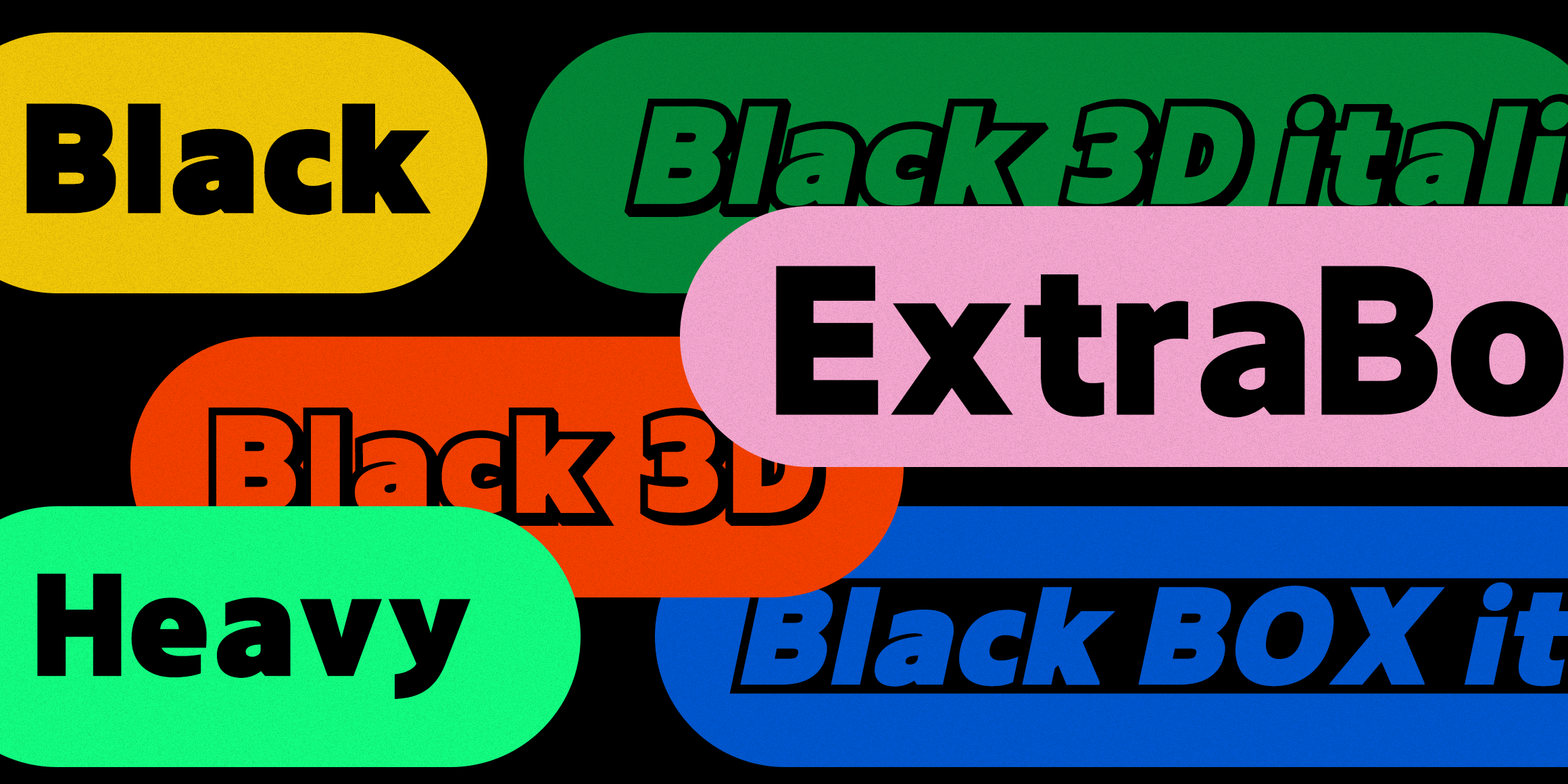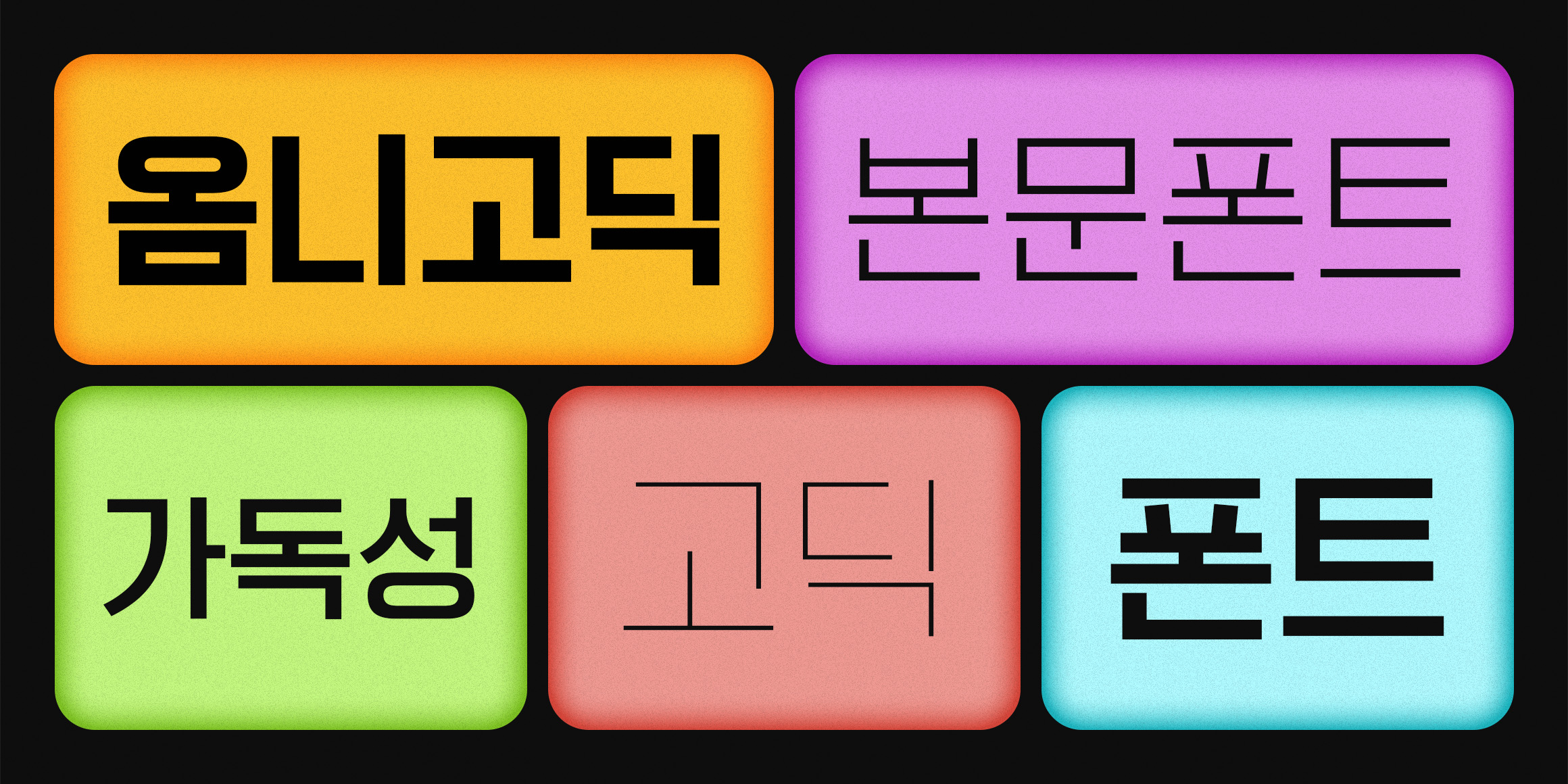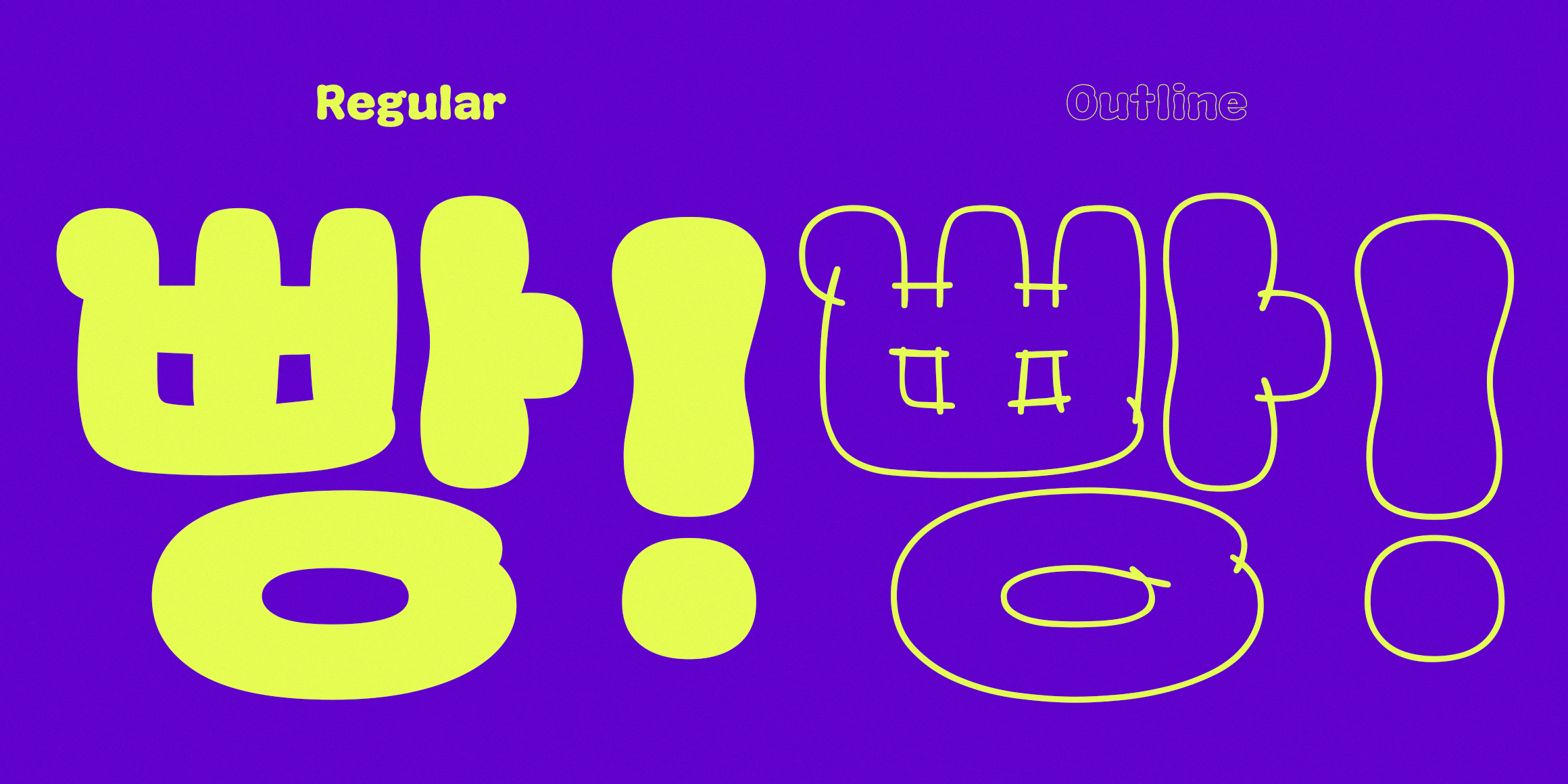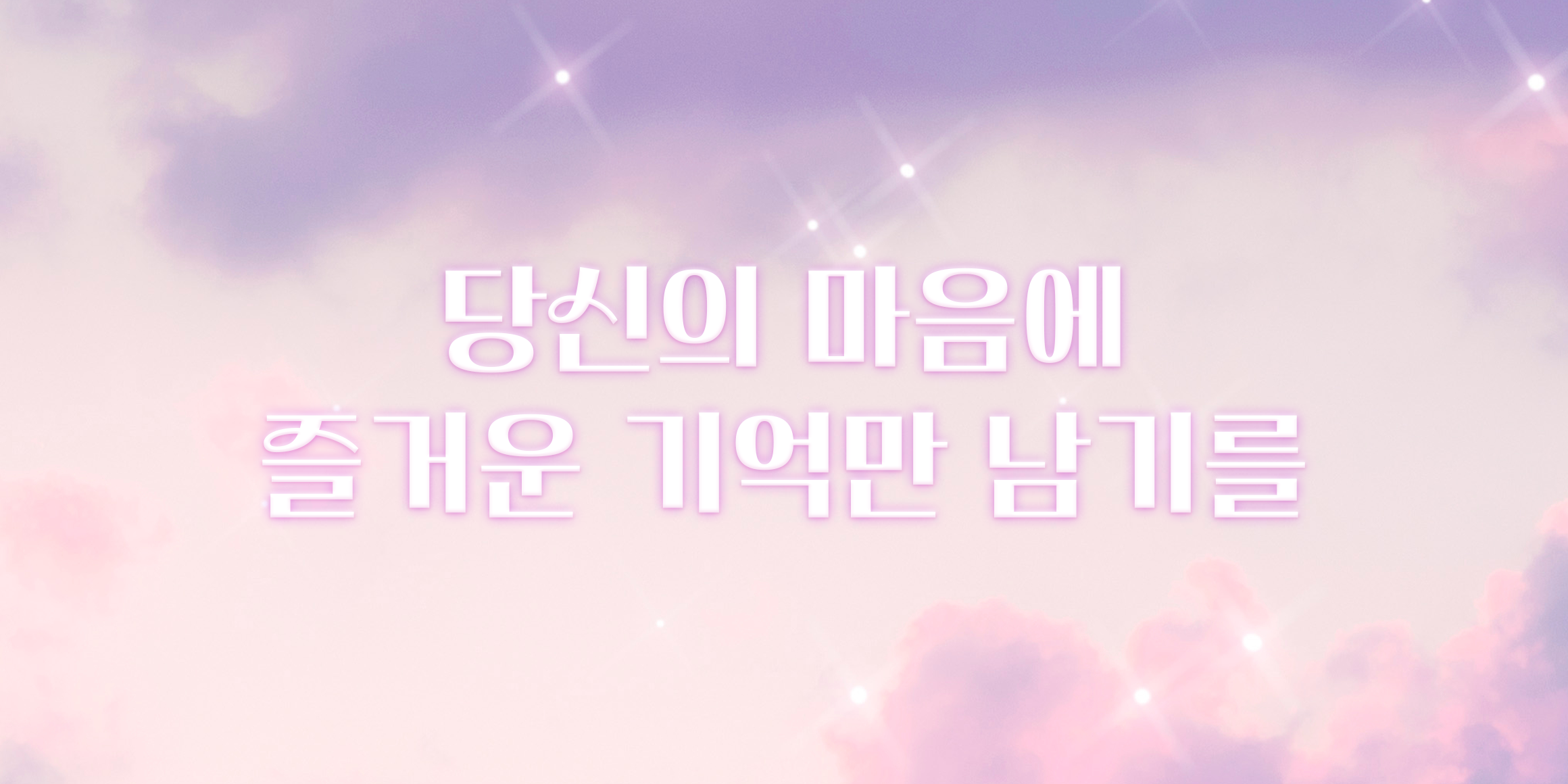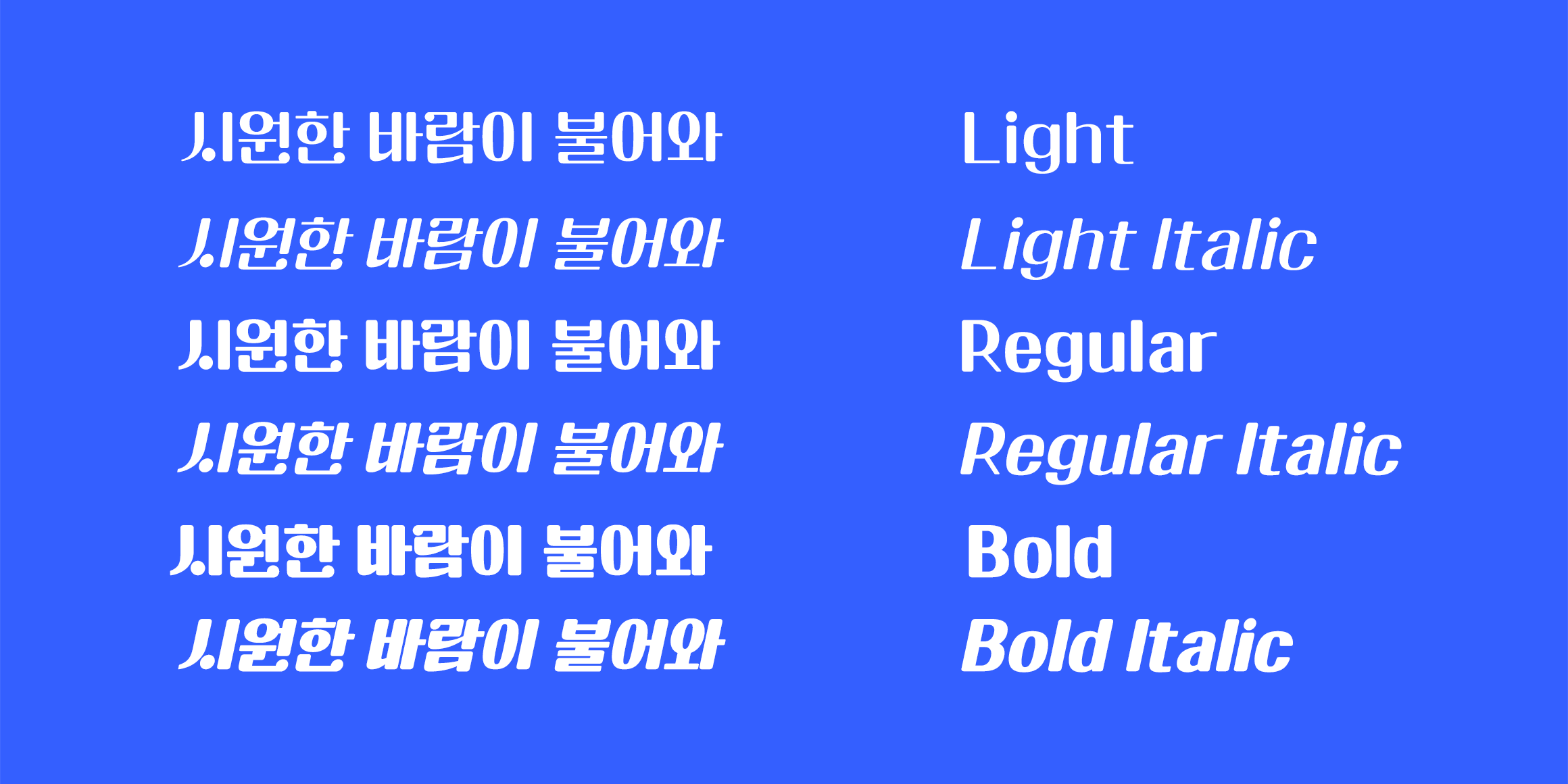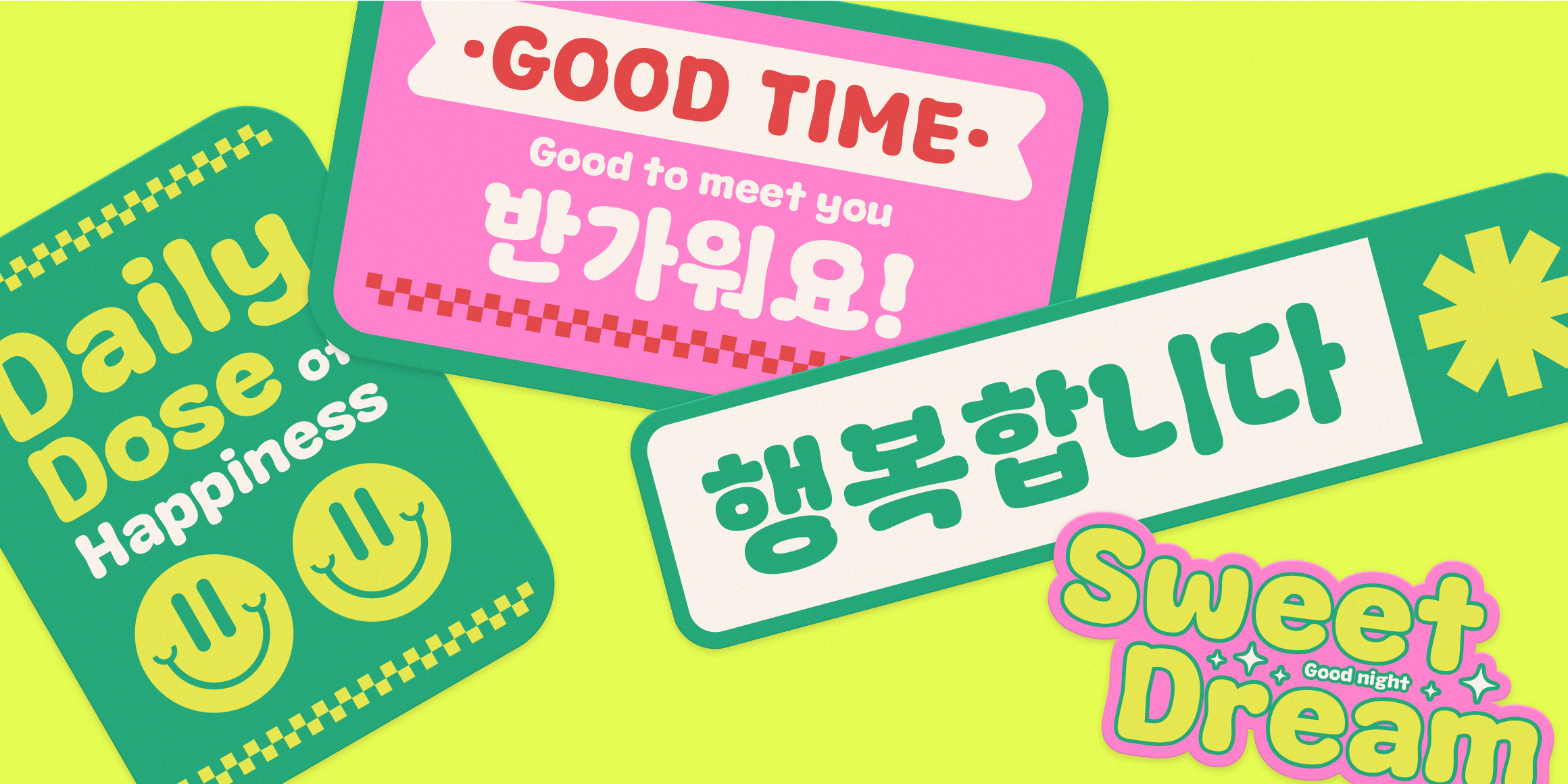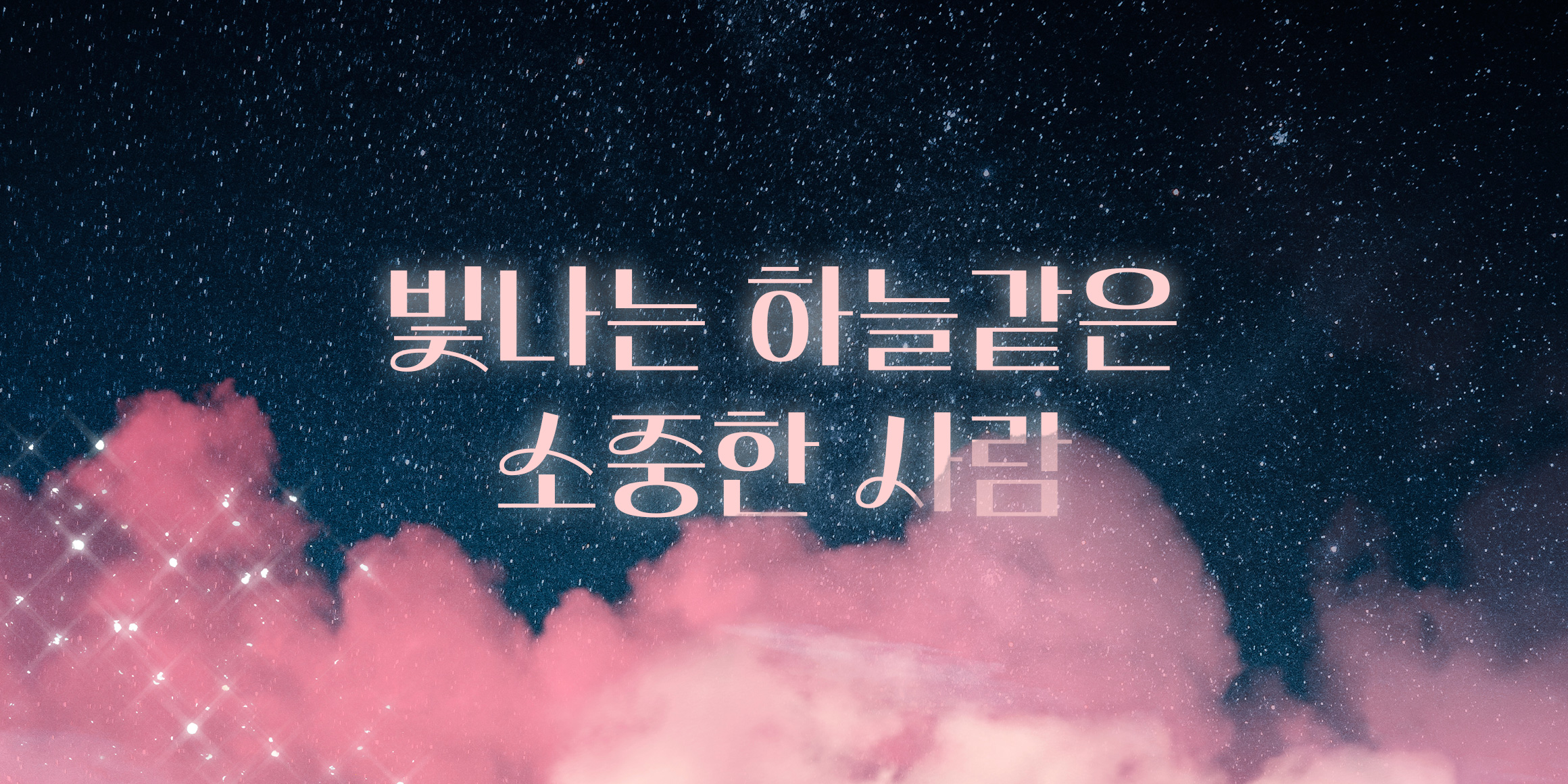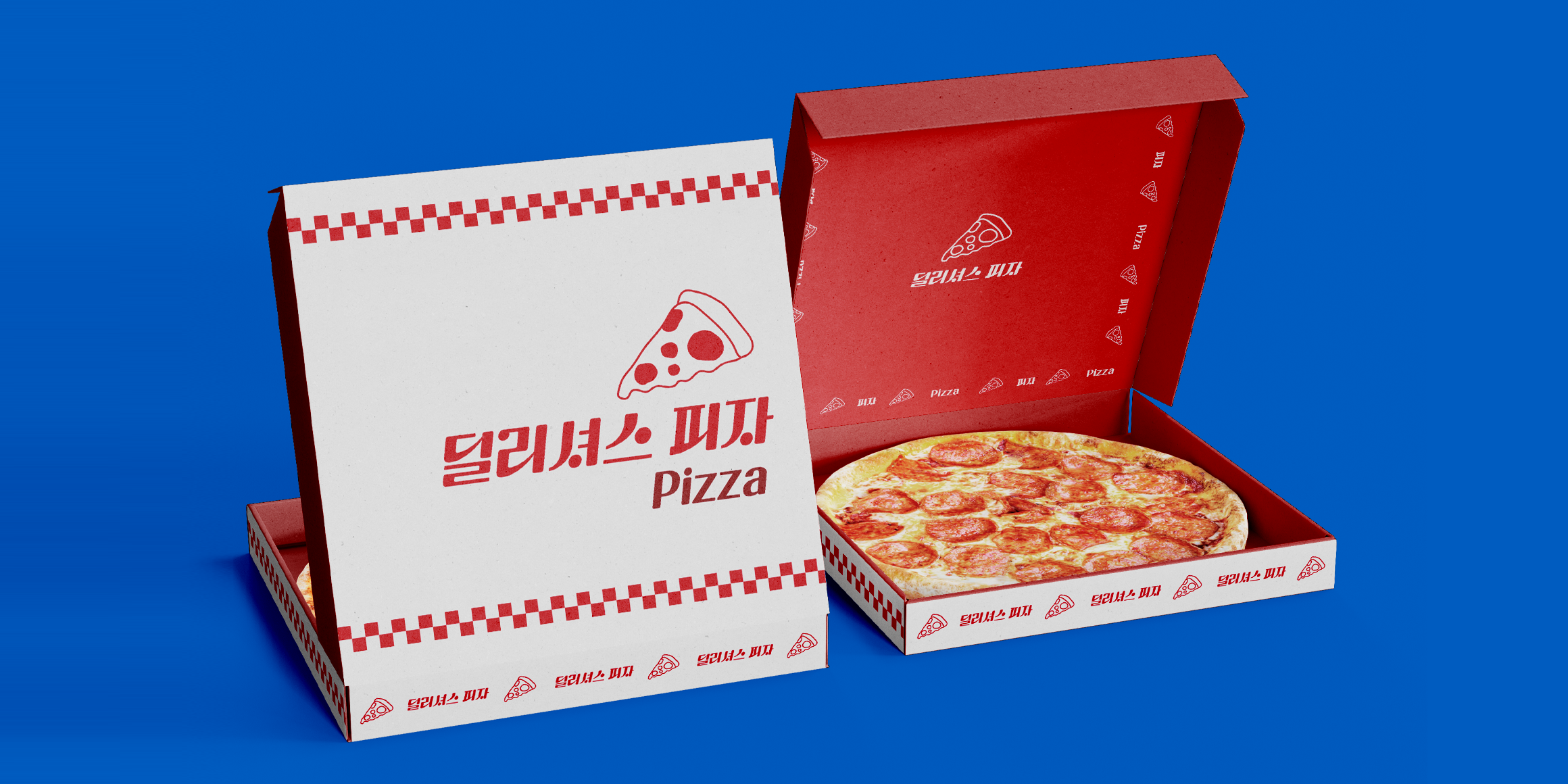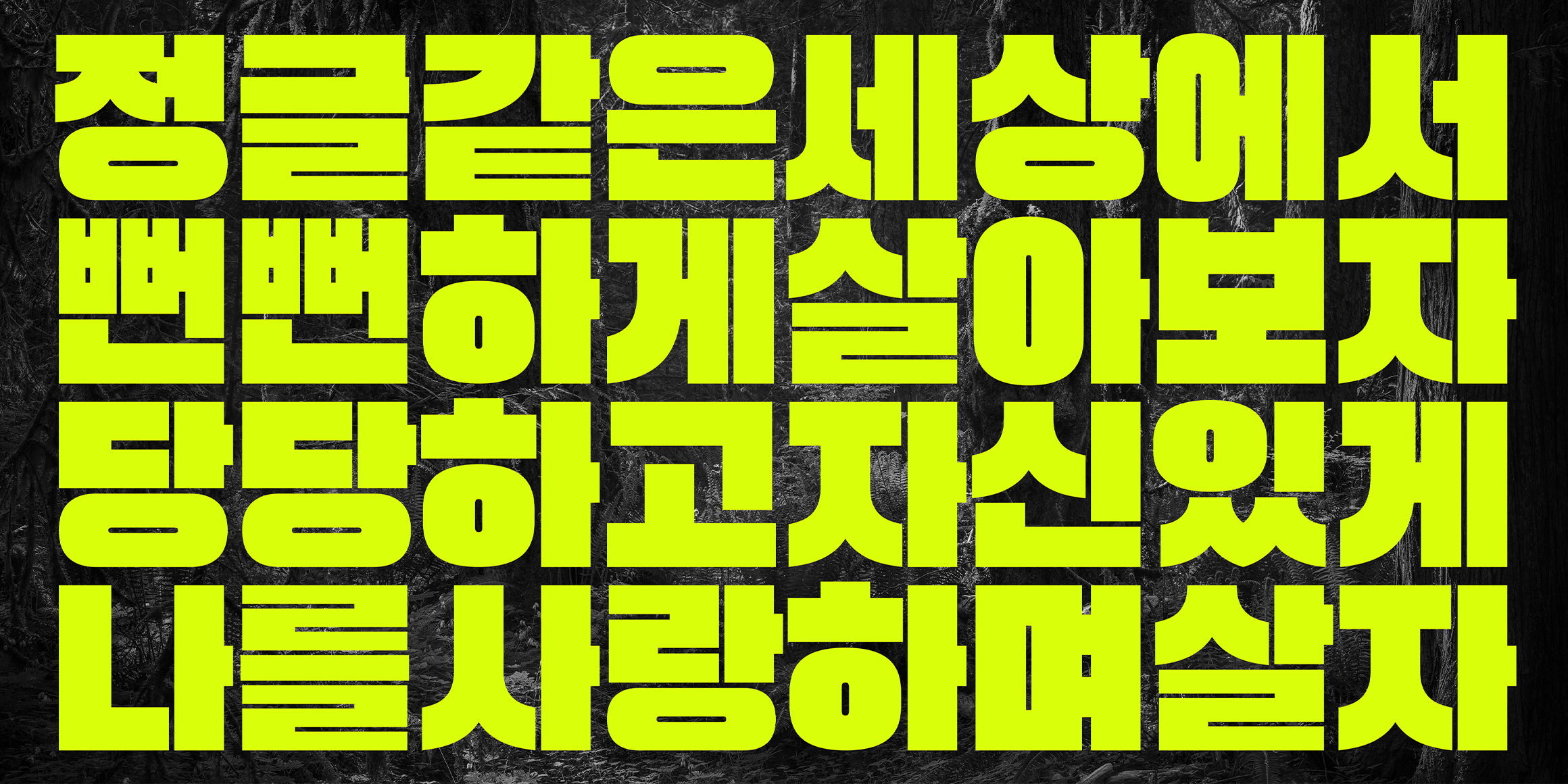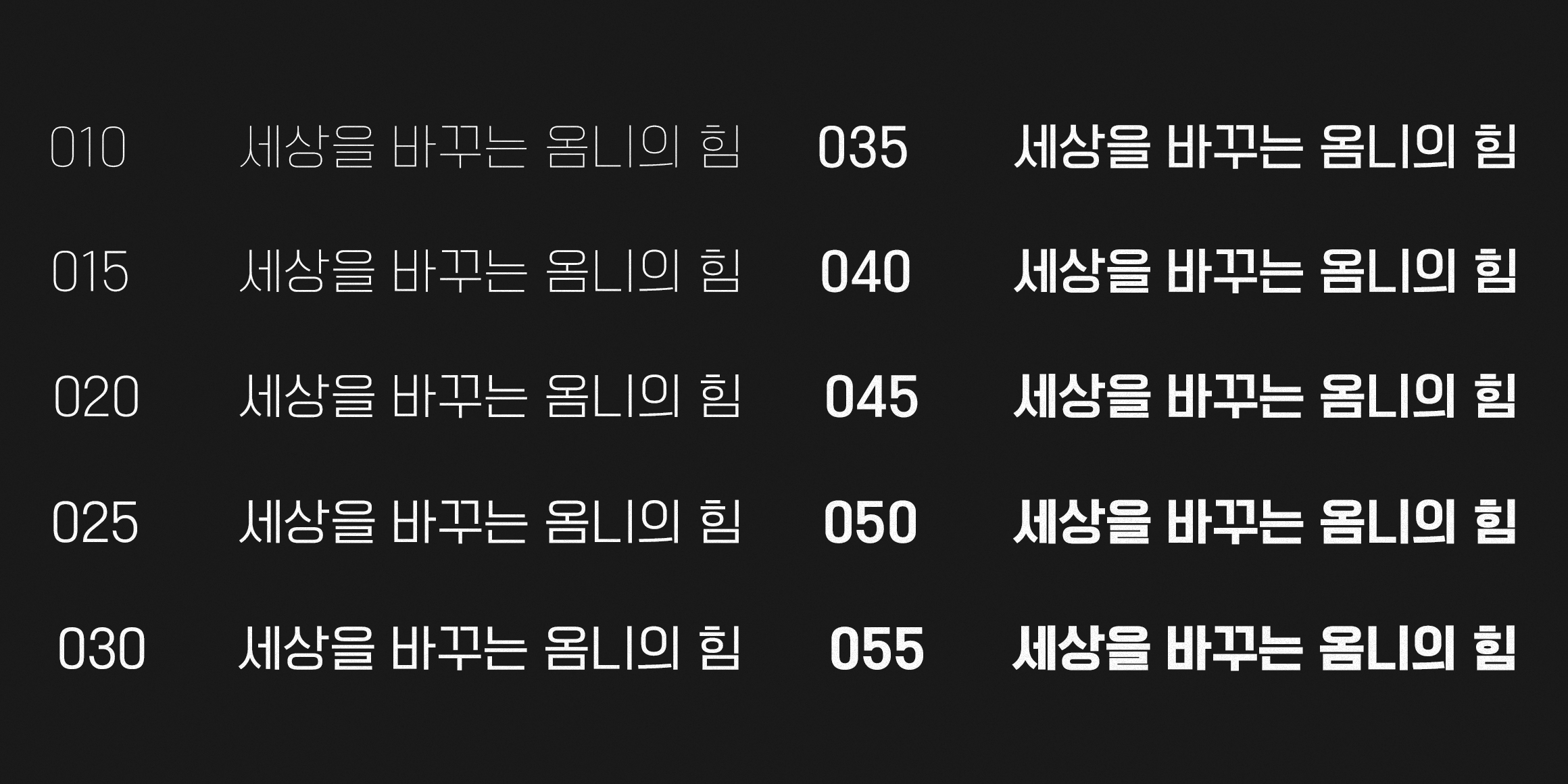
蒙纳宣布收购韩国知名字体公司 DESIGN210,推动高质量字体全球化
2025 年 5 月 14 日,蒙纳正式宣布收购韩国首尔的知名字体厂商 DESIGN210。
此次收购标志着蒙纳在亚洲市场,特别是韩国市场的又一重要布局。
战略布局:拓展韩国市场
为知名韩剧《请回答 1988》定制字体
DESIGN210 拥有逾 1,100 款原创字体,并擅长定制化字体设计,长期为亚洲各大媒体客户提供服务。凭借其高品质、强适应的字体产品,DESIGN210 赢得了包括媒体公司、设计师、广告商在内的广泛认可。
DESIGN210 部分合作客户一览
值得一提的是,DESIGN210 曾凭借为热门手游《Cookie Run》打造的品牌字体荣获 2020 年韩国亚洲设计奖(Asia Design Prize)特等奖,充分体现了其在字体设计领域的专业实力。
此次收购将进一步帮助蒙纳满足全球品牌对高质量韩文字体的需求,并扩大其在东亚市场的影响力。
代表字体:兼具美感与功能
在了解 DESIGN210 代表作品之前,我们不妨首先了解韩文字体的基本分类。
韩文字体主要有两大风格类型:
• 명조체(明朝体),类似于中文的宋体/楷体,相当于西文字体中的衬线体。
• 고딕체(Gothic 体),类似于中文的黑体,相当于西文字体中的无衬线体。
除这两种主要风格外,还有适于特定场景使用的各类手写体与装饰体等。
作为韩国字体设计的佼佼者,DESIGN210 涵盖上述各类风格场景,打造兼具美感与功能的字体,以下为其中五款代表作品:
210 OmniGothic 옴니고딕
一款以可读性为核心打造的正文字体。正如“omni”意为“万用”,OmniGothic 具备极强的通用性,可广泛适用于不同场景与用途。
210 Doughnut 도우넛
Doughnut 是一款以蓬松柔软的面包为灵感设计的字体。整体通过弧线展现出饱满鼓胀的视觉效果,并以方形结构增强辨识度。
该字体家族包括两种风格:Regular,呈现出如夹心甜甜圈般的饱满质感;以及 Outline,通过描边效果营造出立体感十足的外观。
210 Santorini 산토리니
这款字体因方形框架内的饱满设计以及横竖笔画的对比,作为标题使用时极具吸引力。
尤其是“ㅅ”等辅音中的圆形元素,让人联想到圣托里尼的圆顶,为字体增添了独特个性,整体风格更显柔和且富有生气。
210 Supersize 수퍼사이즈
Supersize 是一款为传达强烈视觉印象而设计的字体。其粗重笔画与方正结构营造出厚重感,倾斜角度赋予字体速度感,而 3D 效果则带来视觉冲击。
字体元素醒目有力,并包含多种效果样式,适用于各类场景,堪称一款抓人眼球的多用途字体。
210 Bimiljeongwon 비밀정원
这款字体通过在紧凑结构中加入鲜明的笔画粗细对比,呈现出干净利落且富有格调的视觉感受。同时,字形内部舒展留白,提升可读性;整齐的线条则带来稳定、清爽的整体印象。
而诸如“ㅅ、ㅈ、ㅊ”等字符,设计上采用柔和下垂的曲线,赋予字体独特而有辨识度的个性。